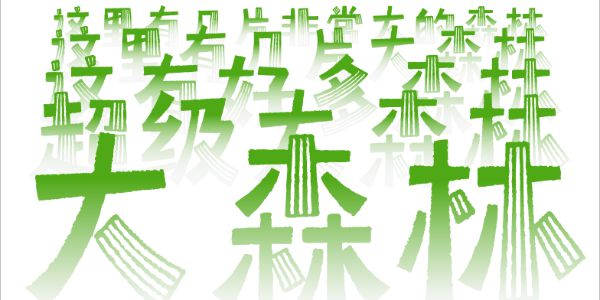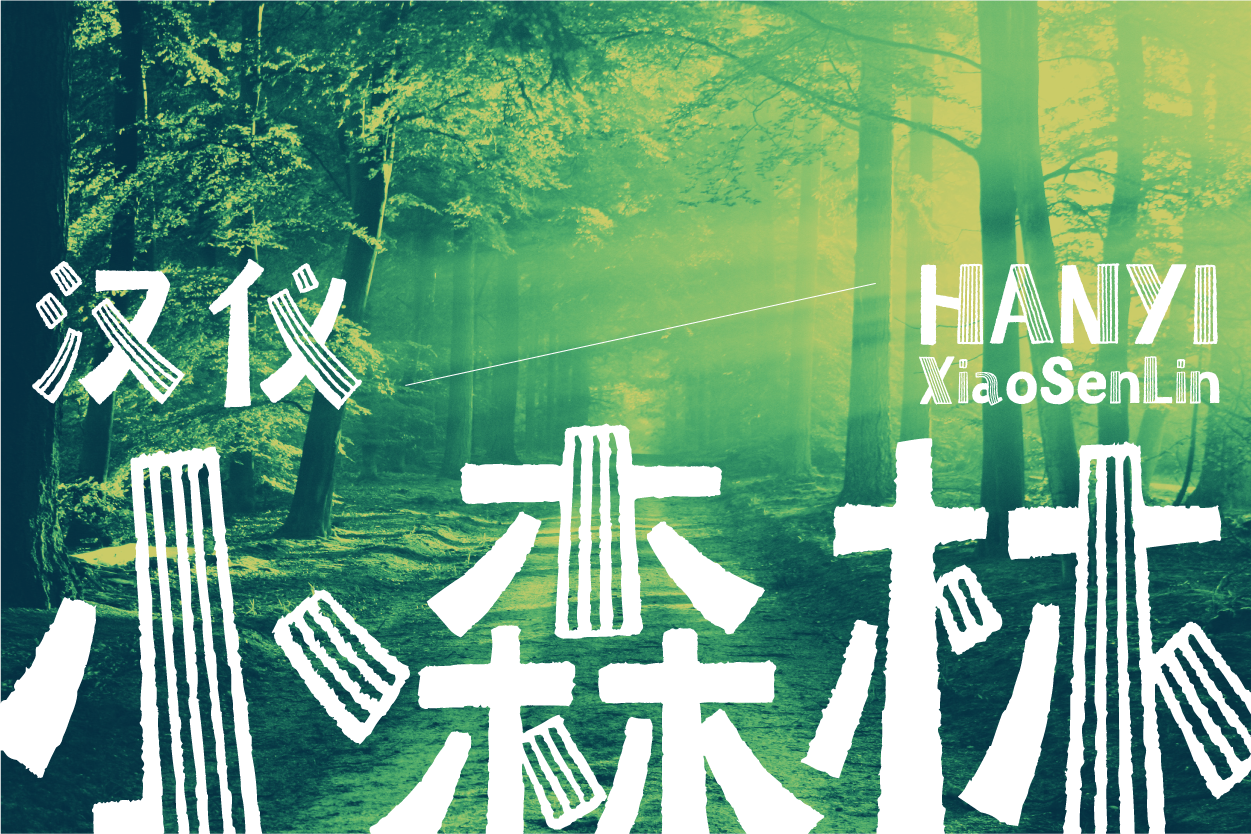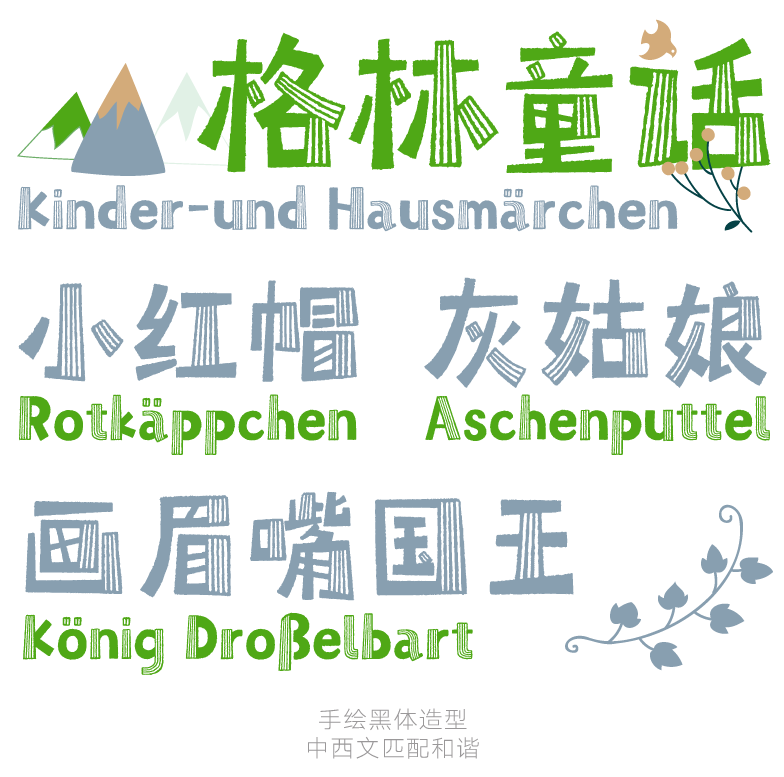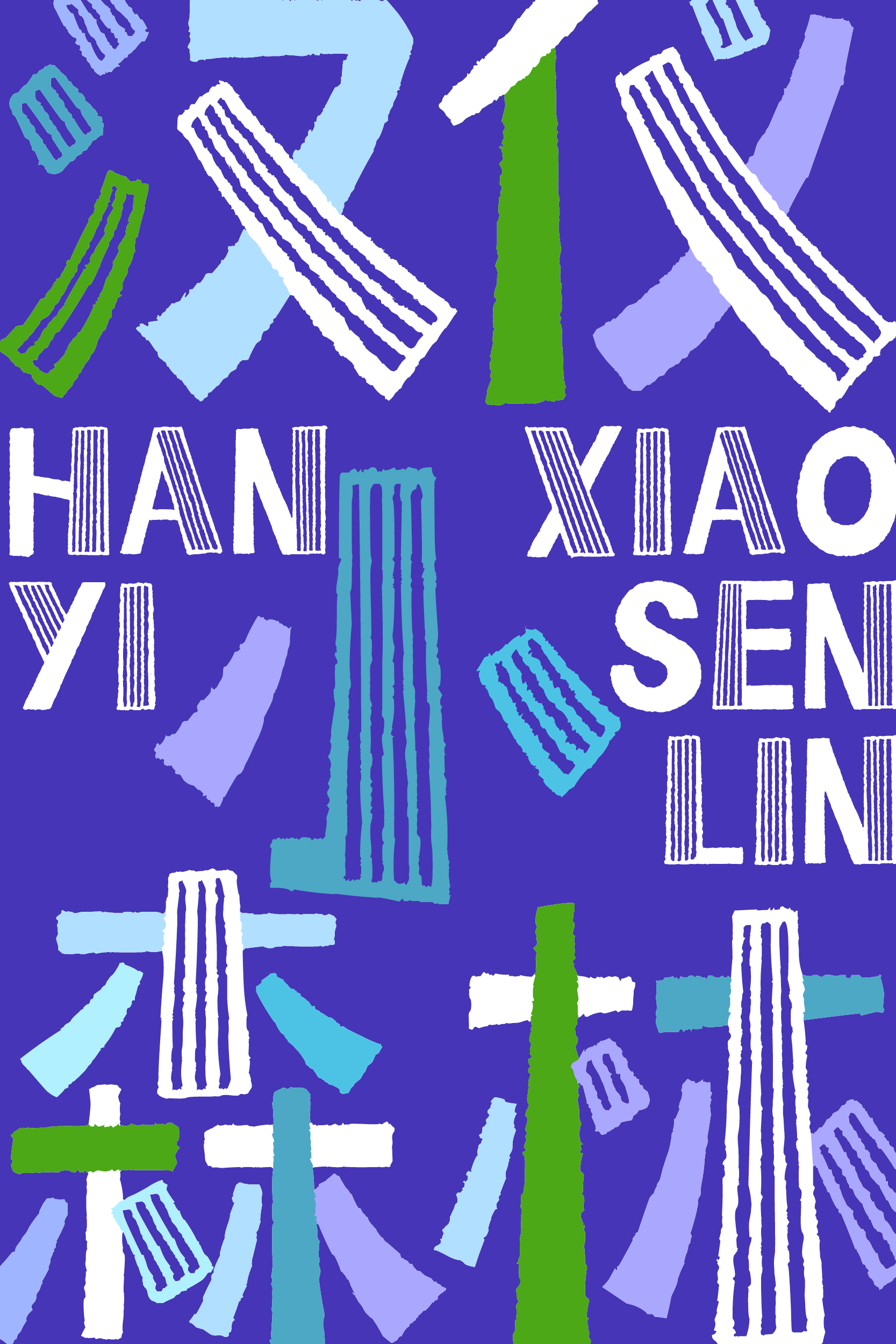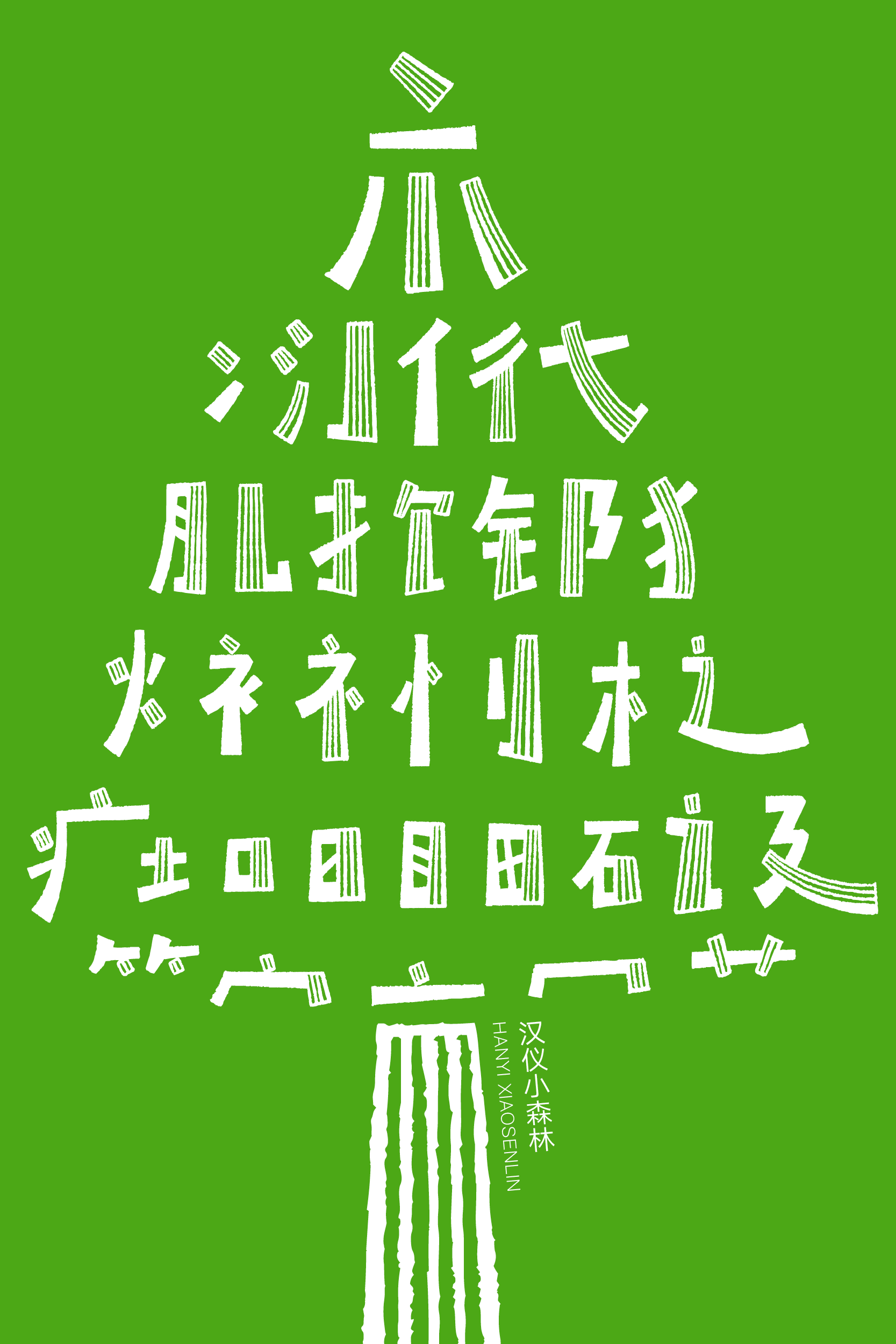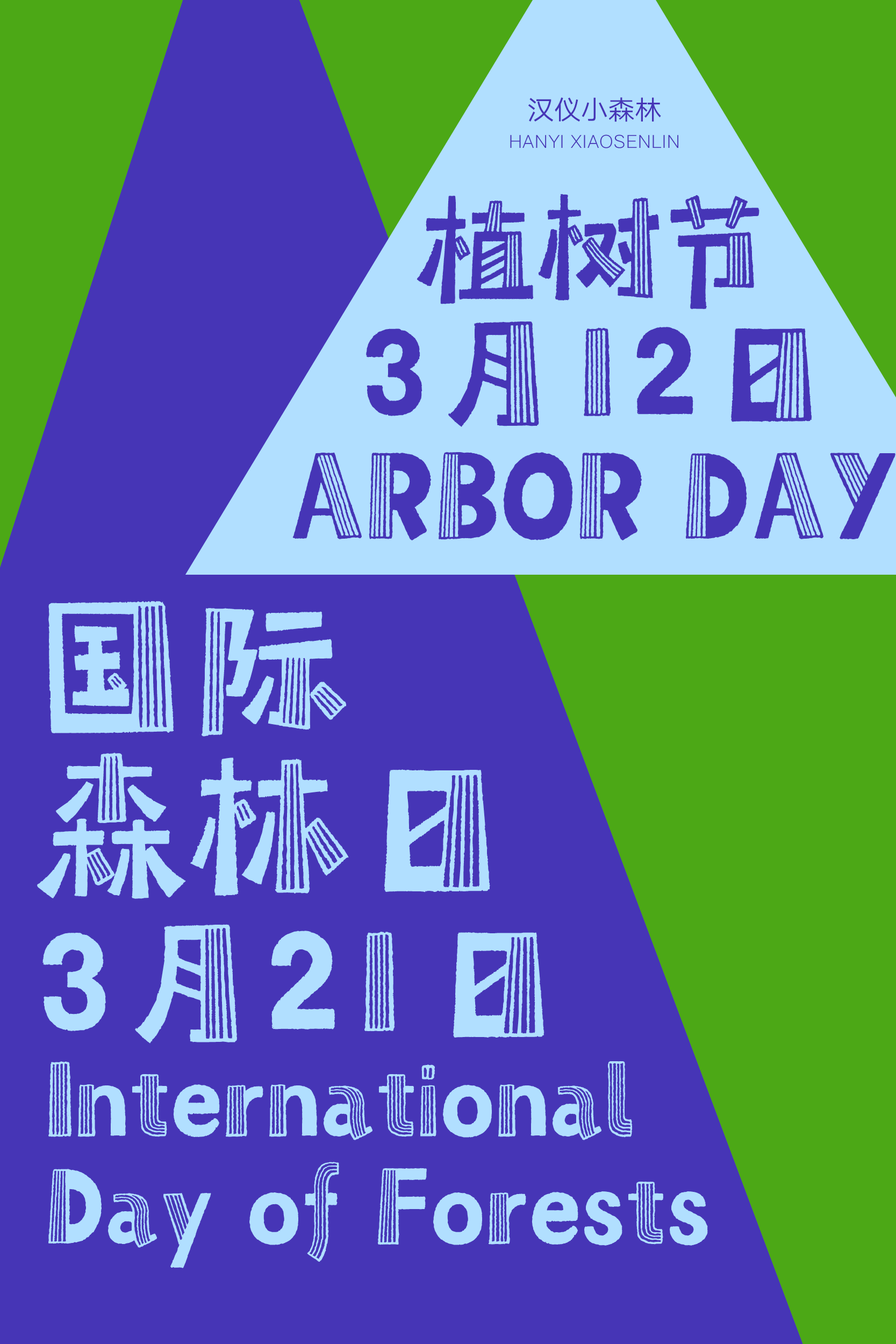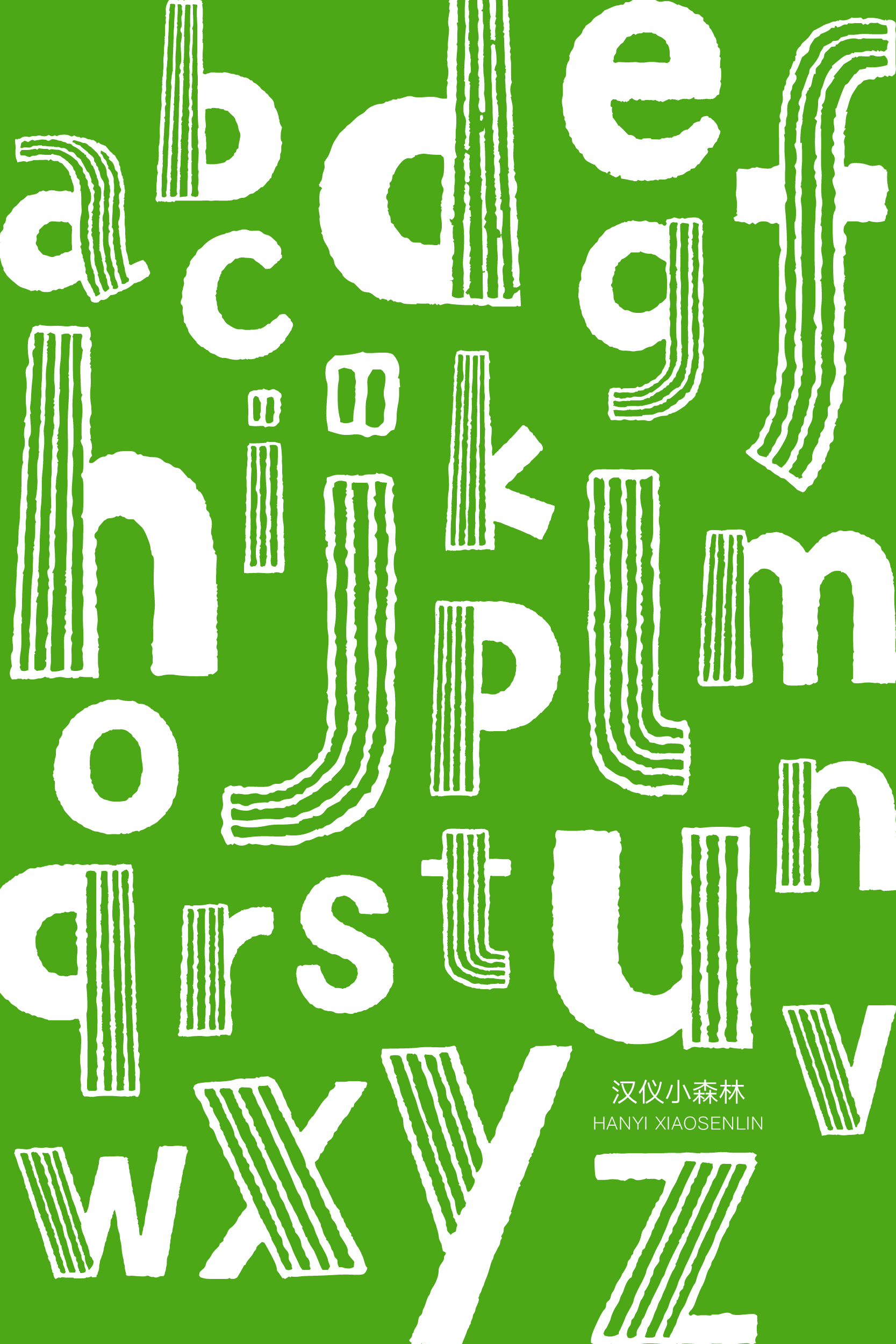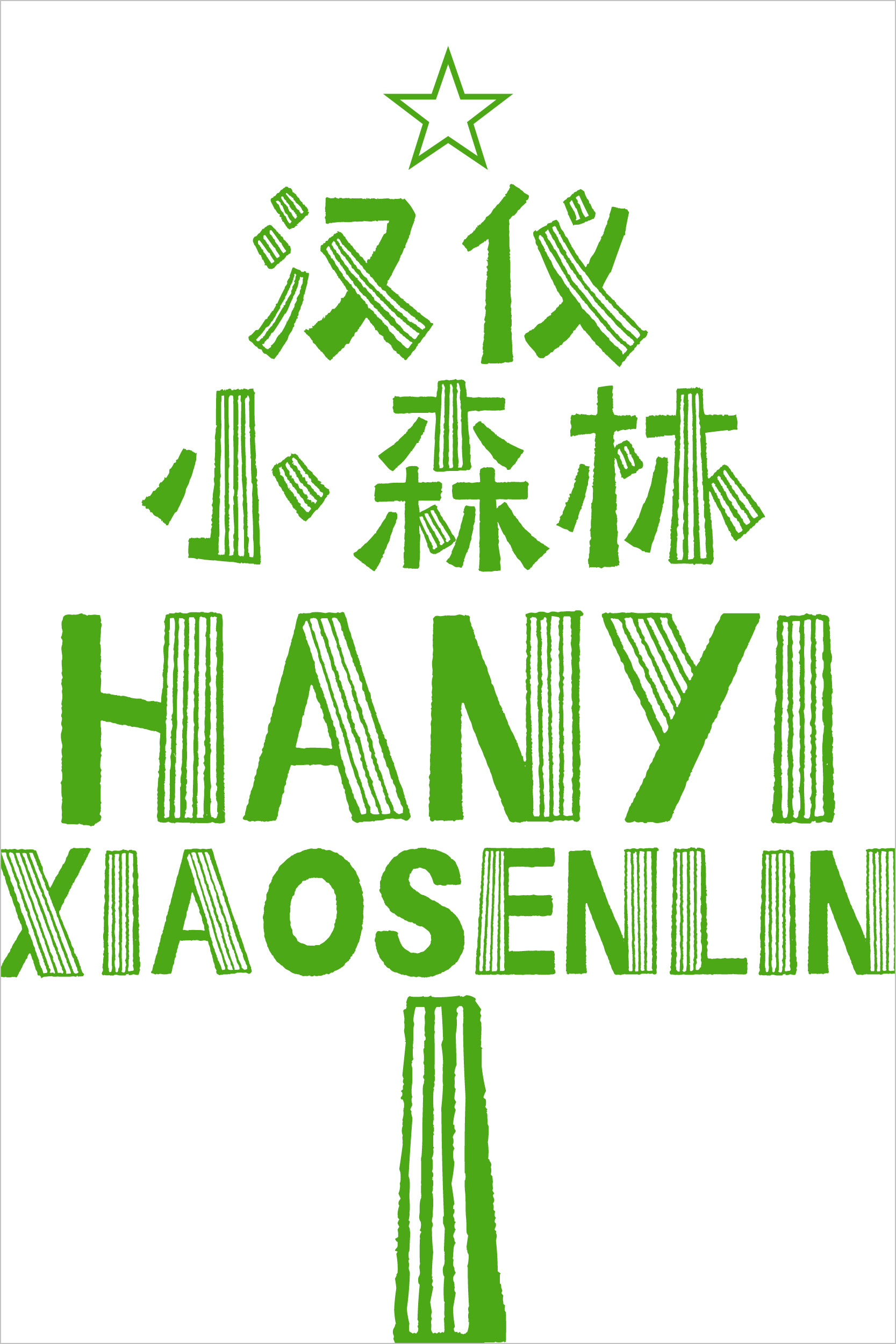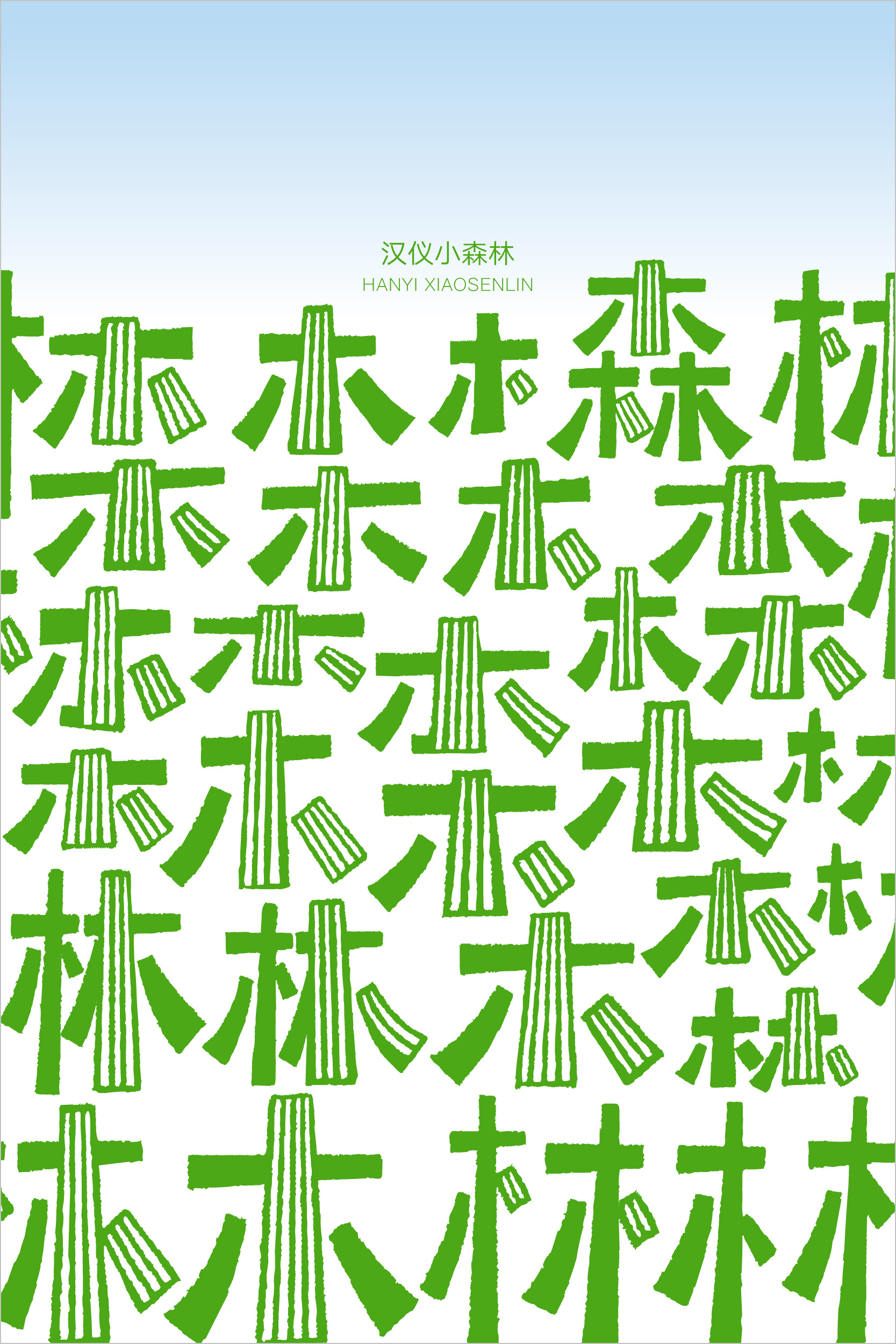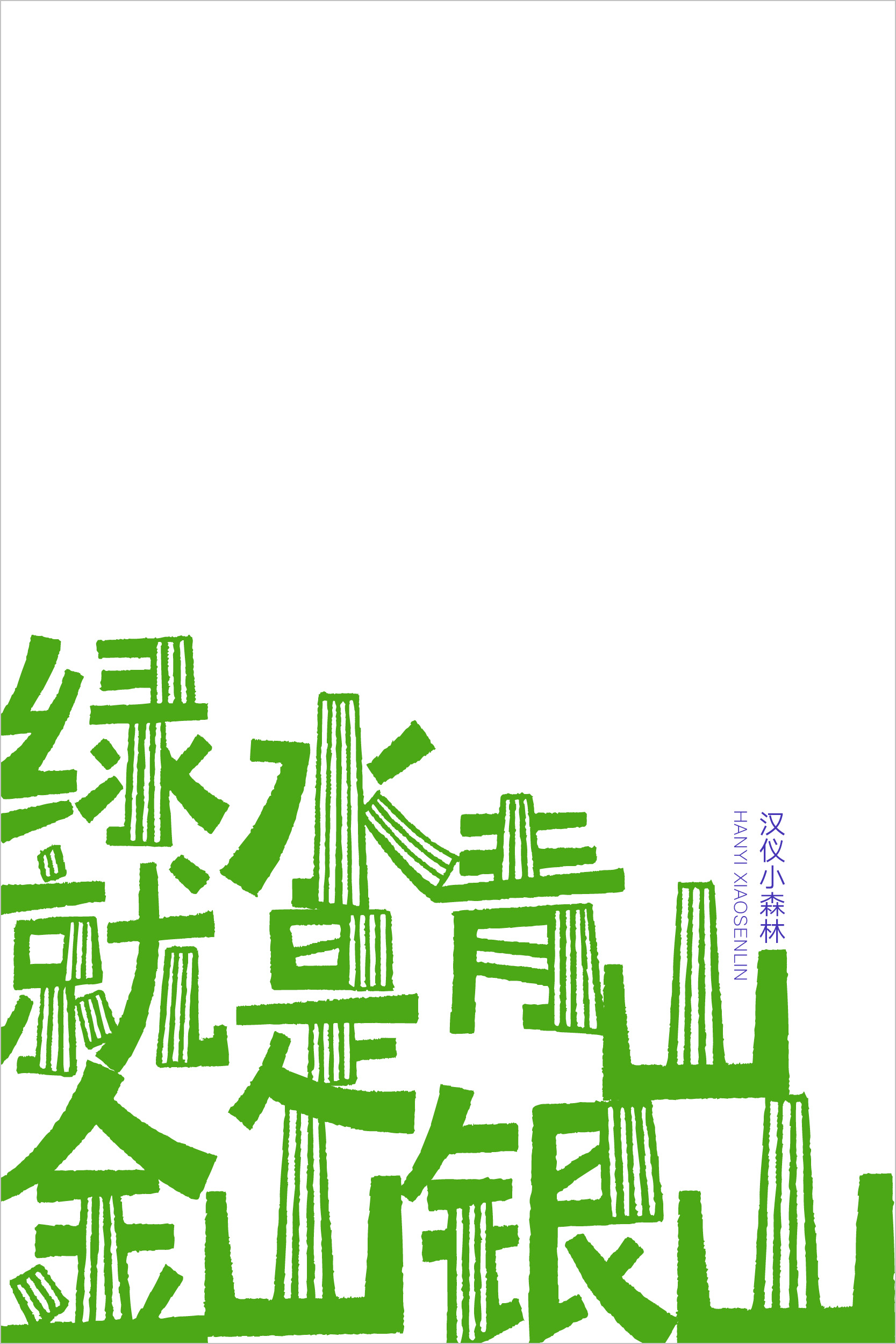
原来小森林也可以是一款字体
清新 / 愉快 / 年轻 / 惬意 / 童话
标志 / 书籍 / 广告 / 杂志 / 游戏 / 动漫 / 影视 / 包装
汉仪小森林是由汉仪字库设计师李佳佳设计的一款手绘字体。该字体散发出清新惬意的气息,如同漫步在童话般的森林中,雾霭出散,初夏的晨光映照下来,透过落满雨露枝桠,漫射在湿润的泥土上,焕发出沁人心脾的清香。该字体适合作为标题字,用在玩具礼品、文创周边、产品包装、综艺海报等场合。
汉仪小森林采用简洁明了的笔画设计:所有笔画都由直线或曲线构成,起笔收笔平直简洁,折角明快直接,勾提笔画直角化处理俏皮可爱。
该字体笔画有着明显的粗细变化:主要笔画与次要笔画有着明显粗细对比;每一个笔画本身也有明显的粗细变化。
这款字体在字形的纵向主笔画上做了镂空装饰,以营造树干的肌理。笔画边缘如软嫩的泥土般粗糙有质感,以营造温馨惬意的气氛。字形排版后,能够给人走进青翠的森林一样的感受。
该字体的结构生动灵活:充满粗细变化的笔画使得字形看起来有种被风吹动的摇摆感;部分字形采用了美术字常用的变形手法,使得字形看起来更加俏皮可爱。
汉仪小森林的西文部分也是由设计师李佳佳绘制的。西文部分选择了带有手绘感的黑体造型,并采用与中文同样的设计手法:镂空纹理以及粗糙的肌理。西文部分在气质上比中文部分要更俏皮显可爱一些。